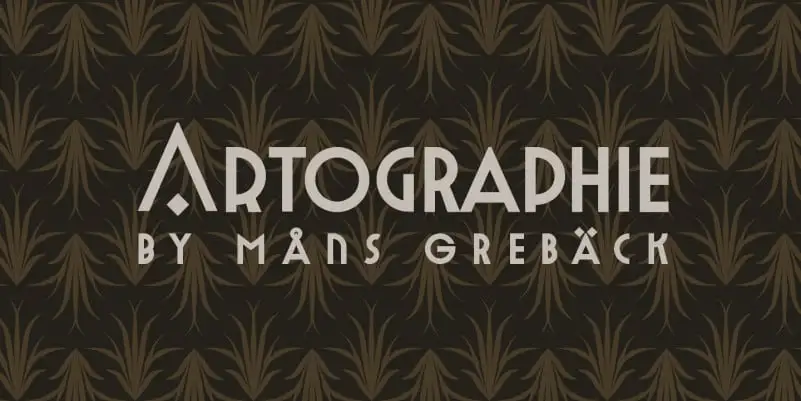
Através da introdução do Artographie Display Font, você encontrará uma experiência visual inovadora que combina a elegância moderna com o encanto vintage. Desenvolvida por Måns Grebäck entre 2019 e 2020 através do site de criações 99designs, esta fonte Sans Serif oferece um olhar arredondado em uma tipografia clássica que já percorreu um século. Com uma personalização adaptada para o uso contemporâneo, a Artographie Display Font é um ícone moderno que reinterpreta estilos de design centenários para atender às necessidades e tecnologias de hoje. Suas linhas retas e elegantes criam um contraste perfeito com uma personalidade vintage reconfortante, tornando-a ideal para aplicativos visuais diversos, desde grandes títulos de negrito até subtiles mensagens gráficas. Sem dúvidas, ela é a escolha perfeita para quem busca unir memória e modernidade em cada projeto visual.